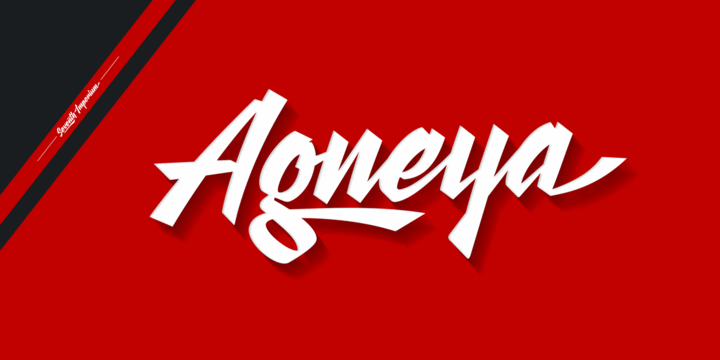
Agneya font – Fonte Grátis
Agneya font
A Agneya font é uma elegante escolha para quem deseja adicionar um toque único à sua tipografia. Esta fonte, cuidadosamente criada pelo designer Hamilton, oferece linhas finas e delicadas que se adaptam perfeitamente a qualquer projeto de escritura chinesa ou outros estilos similares. Com uma combinação harmônica de cores suaves e formas sutis, essa font é ideal para trabalhos que exijem um grau elevado de cuidado em sua apresentação. Perfeita para designers gráficos atentos à detalhe, a Agneya promete revitalizar seus projetos com uma pitada de sofisticação sem exigir muito esforço adicional. Não importa se você está criando arte digital, letras chinesas ou qualquer outro tipo de projeto que exige um toque refinado, a Agneya font certamente será sua escolha ideal.